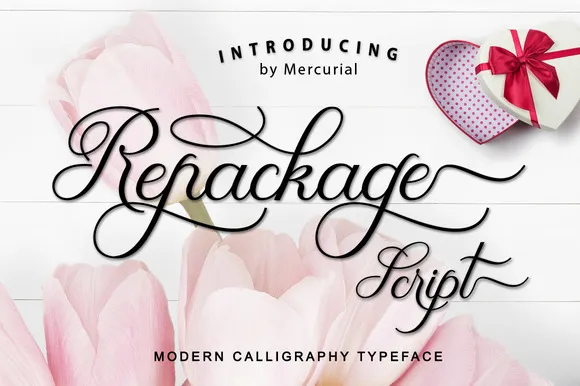
Repackage Script Font – Download Grátis
Introduzimos a Repackage Script, uma nova e moderna tipografia script com um estilo de caligrafia feita à mão. É uma face elegante e sofisticada que traz grande beleza para cartões de convite ou cartas de cumprimentos, materiais de marca, cartões de visitas, frases curtas, panfletos, e muito mais! Ideal tanto para designers buscando algo moderno quanto para aqueles que desejam um toque de personalidade tradicional em suas criações. Com certeza, Repackage Script é a escolha perfeita para quem procura uma fonte com estilo único e sofisticado para seus projetos de design gráfico.